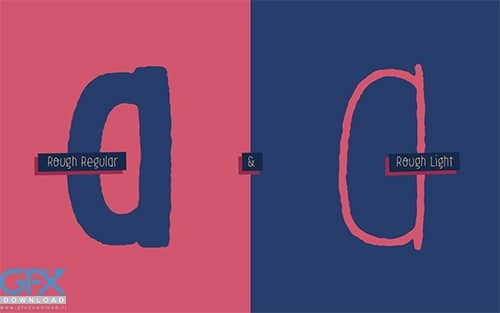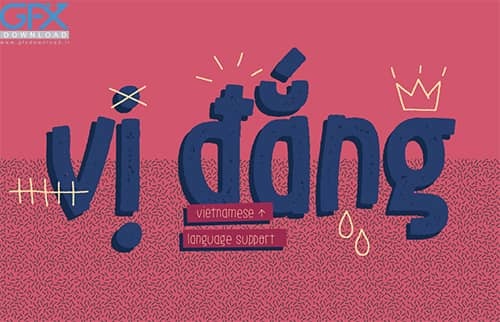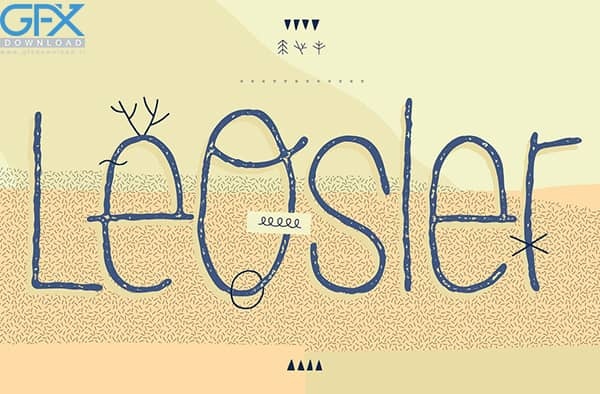
فونت رایگان تزئینی انگلیسی LeoSler
فونت انگلیسی LeoSler
دانلود رایگان فونت تزئینی انگلیسی زیبا LeoSler
این فونت مناسب برای سبک های شارپ می باشد. LeoSler یک فونت تزئینی ، سرگرم کننده و دست نویس است که ظاهری شخصی به کار شما می بخشد. این فونت شامل الفبای لاتین ، یونانی و سیریلیک است و می تواند در طیف وسیعی از زبانها از جمله انگلیسی ، اسپانیایی ، ایتالیایی ، فرانسوی ، آلمانی ، لهستانی ، چک ، ویتنامی ، روسی ، یونانی و غیره استفاده شود. فونت رایگان تزئینی انگلیسی LeoSler شامل پیوندها برای همه حروف بزرگ و کوچک تکراری ، متون جایگزین برای همه حروف پشتیبانی شده ، 4 حرف بزرگ متناوب ، ارقام علمی بالا / پایین ، کسرها و غیره است. LeOSler همچنین مجموعه ای از آیکون ها را ارائه می دهد که ظاهر بسیار شخصی تری به کار شما می بخشد! موجود در سبک های Regular و Light ، Rough و Stamp.